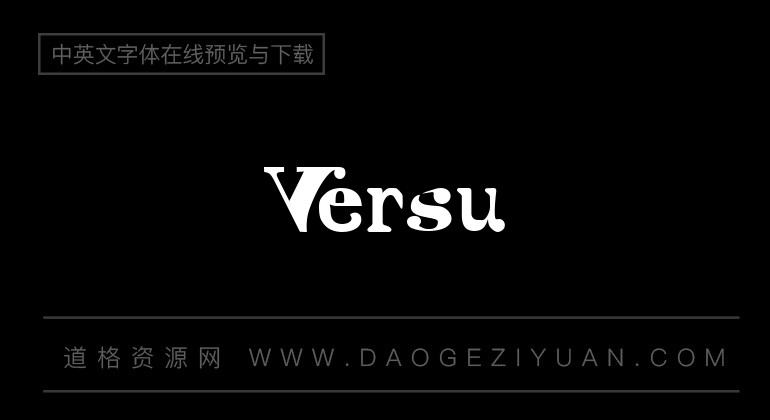
Versu
? Versu 字体是一款现代、优雅的字体,它的设计灵感来自古典的拉丁文字体,它的笔画更加柔和,更有节奏感,使其成为一款非常适合用于设计和出版的字体。Versu 字体具有清晰的笔画,它的字母具有精细的细节,可以更好地表达您的想法,让您的设计更加有趣。Versu 字体适用于各种场合,从广告到网页,从简笔画到复杂的图形,都能完美地表达您的设计。
Versu是一款非常不错的手写艺术字体,具有很好的视觉感,适合于文化类的宣传设计、商业类品牌的广告和产品包装设计以及个性化文字排版等较多场景。